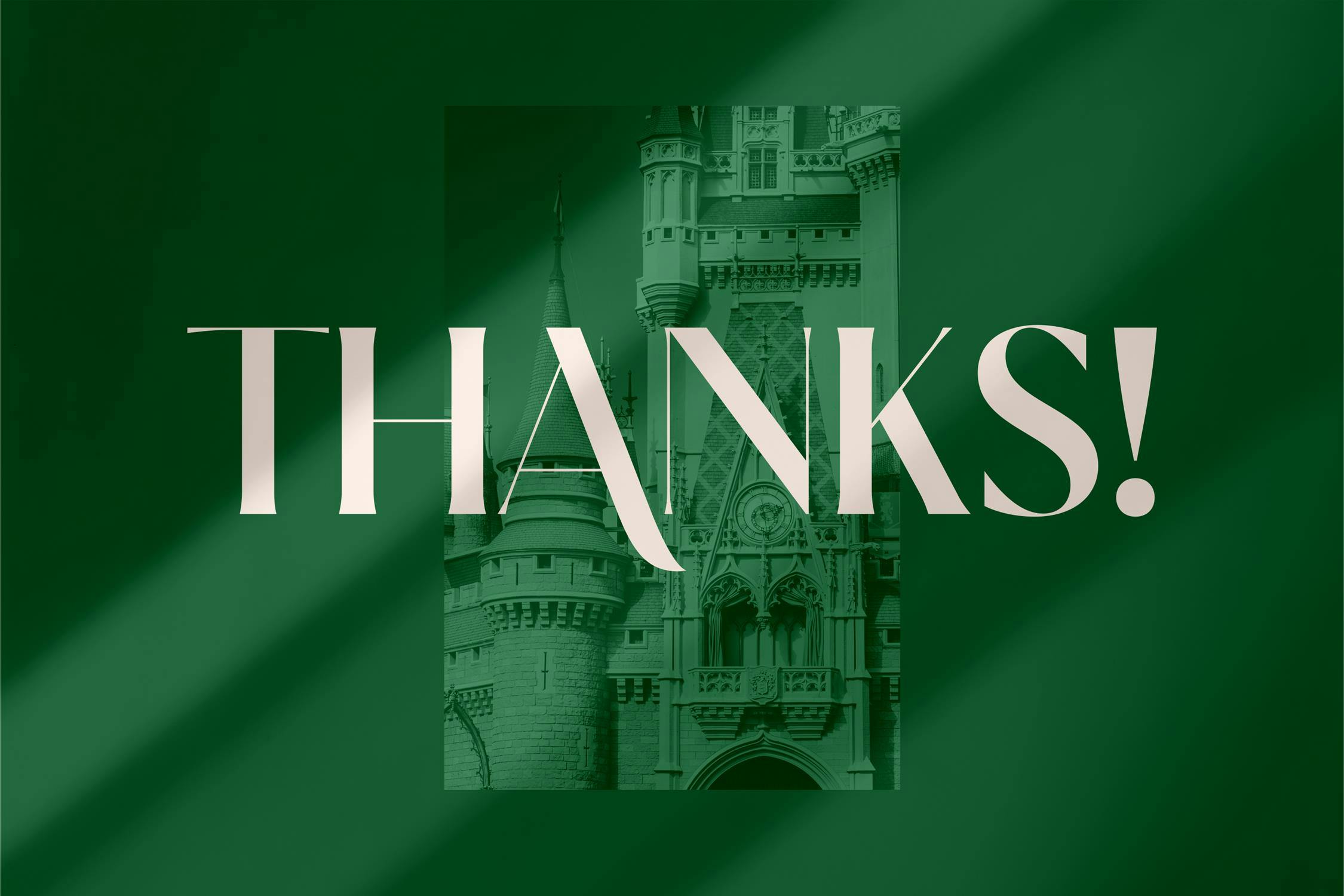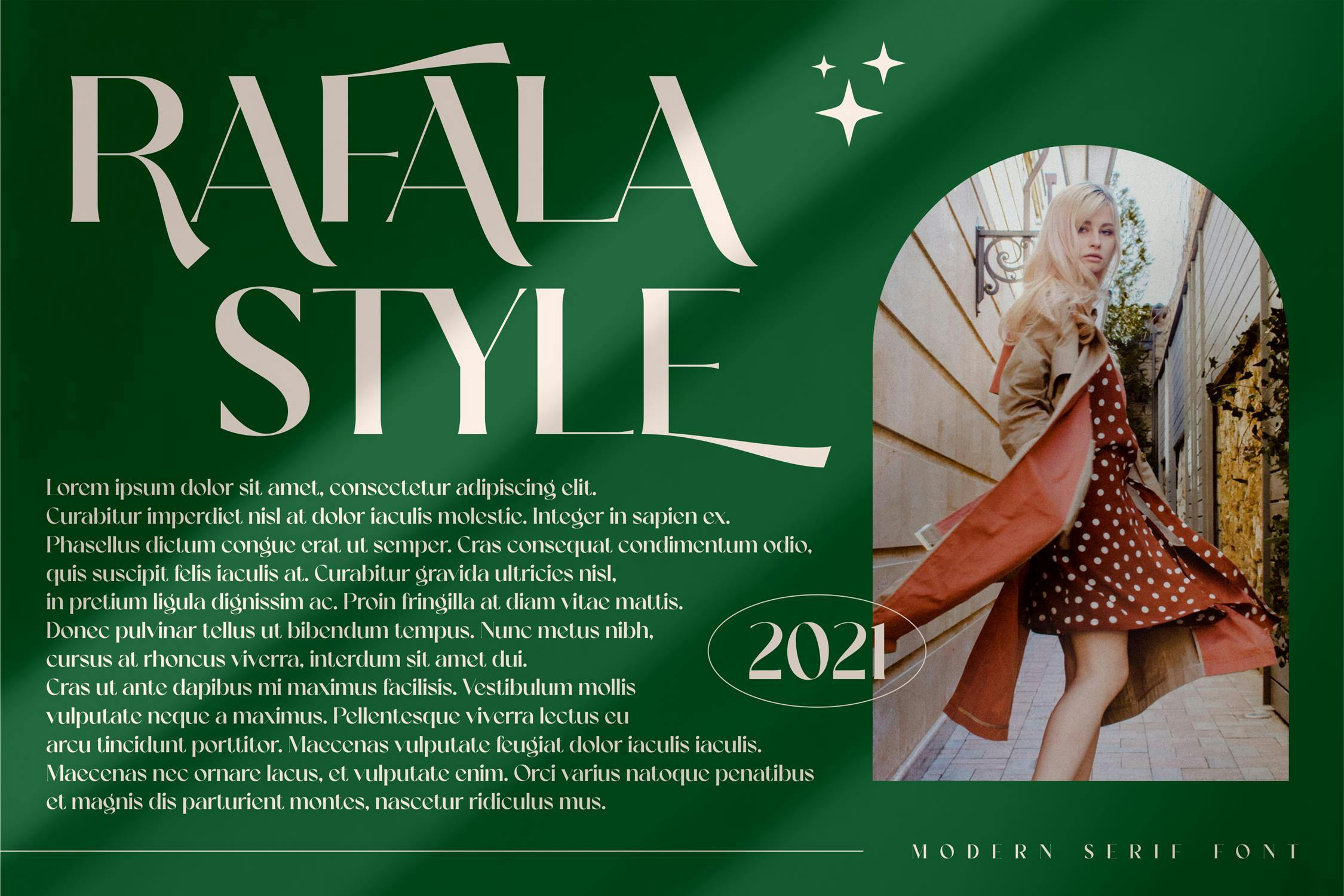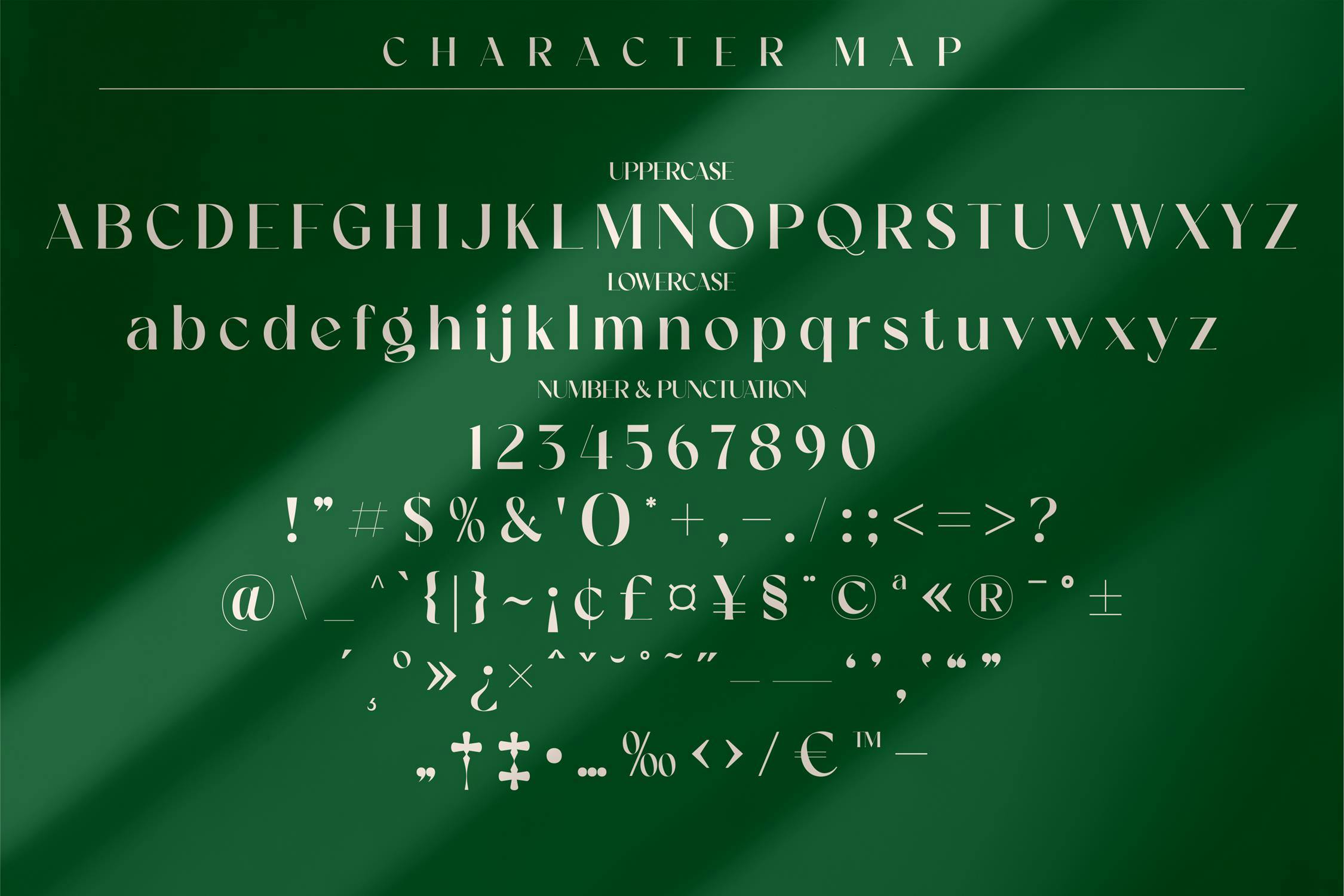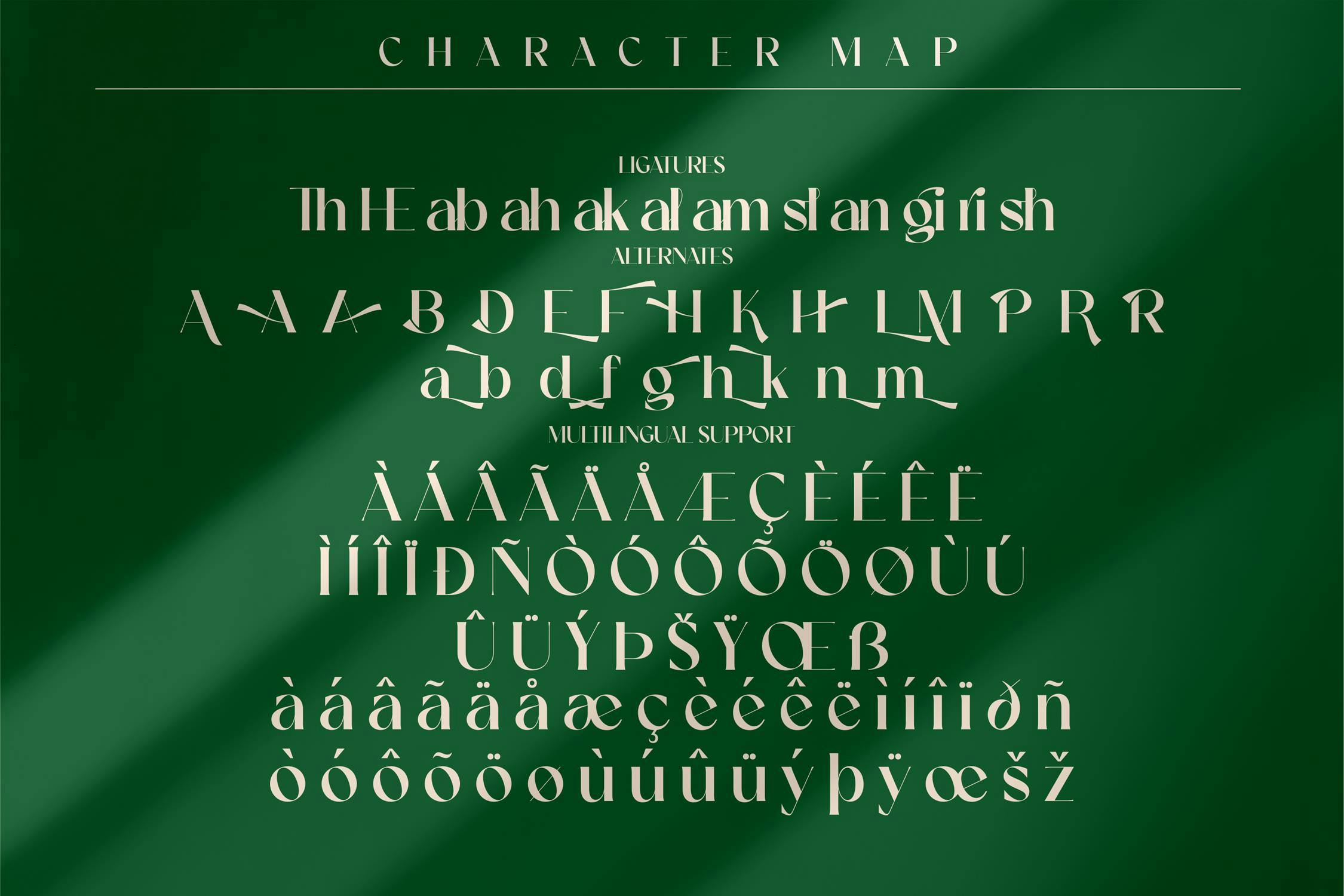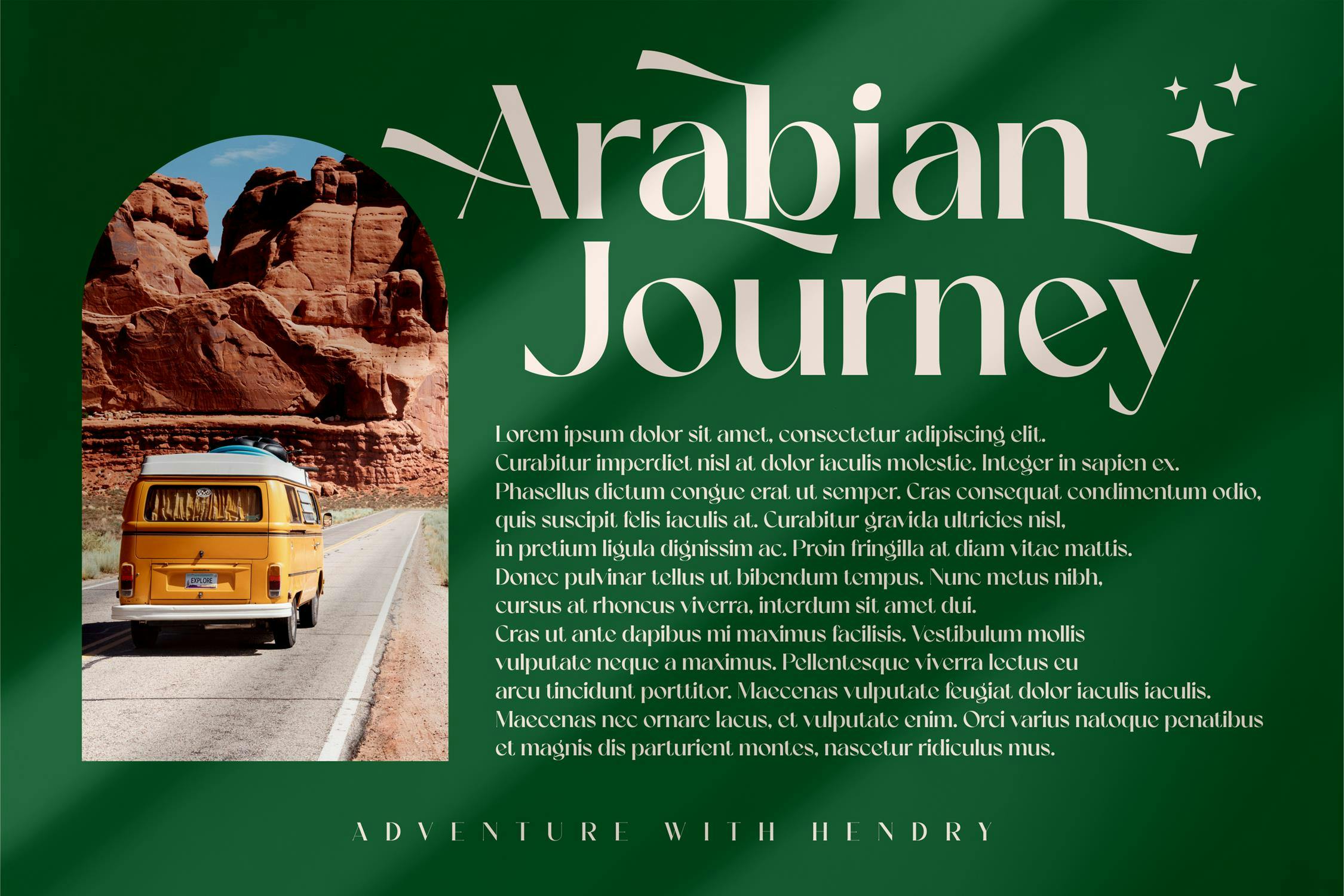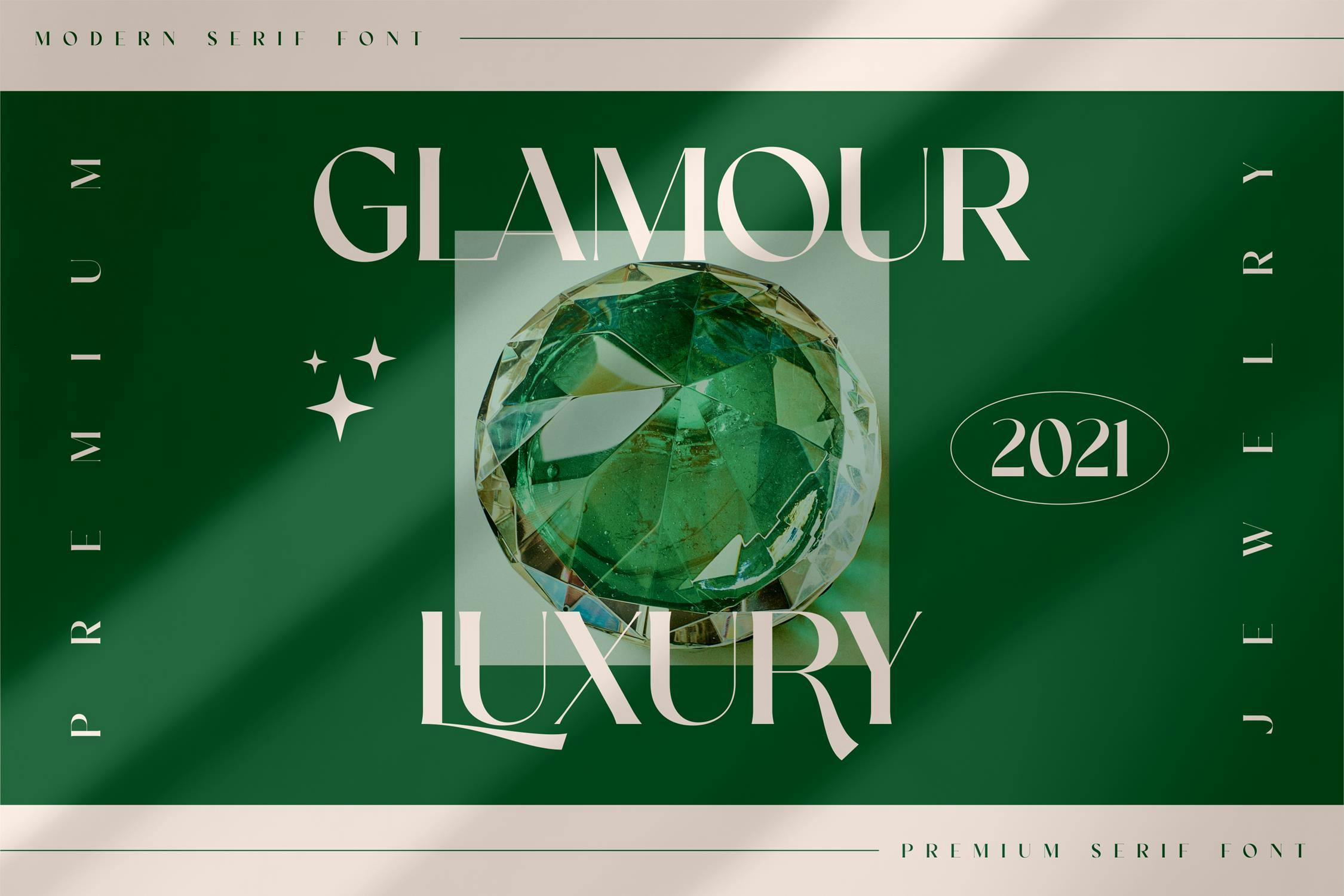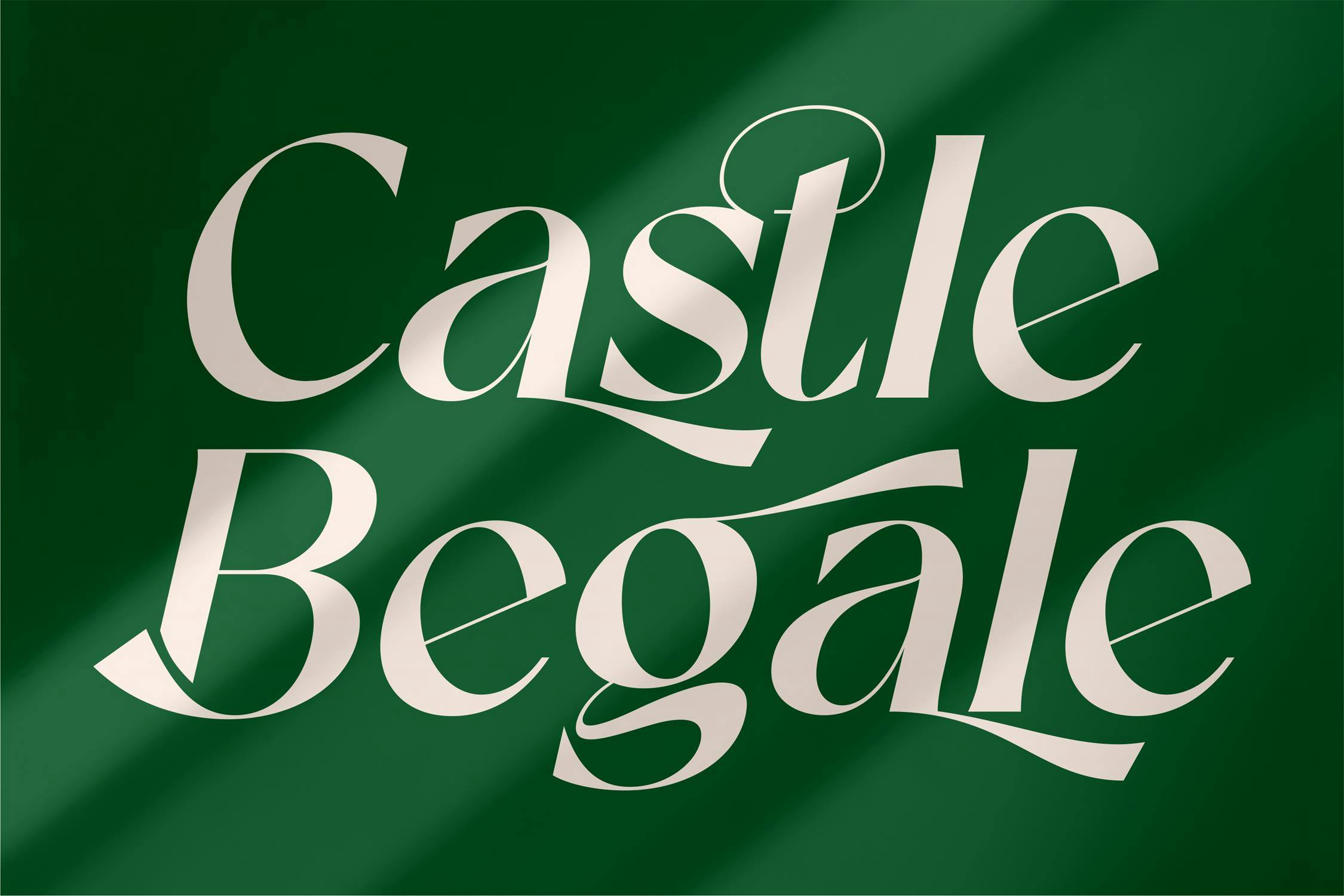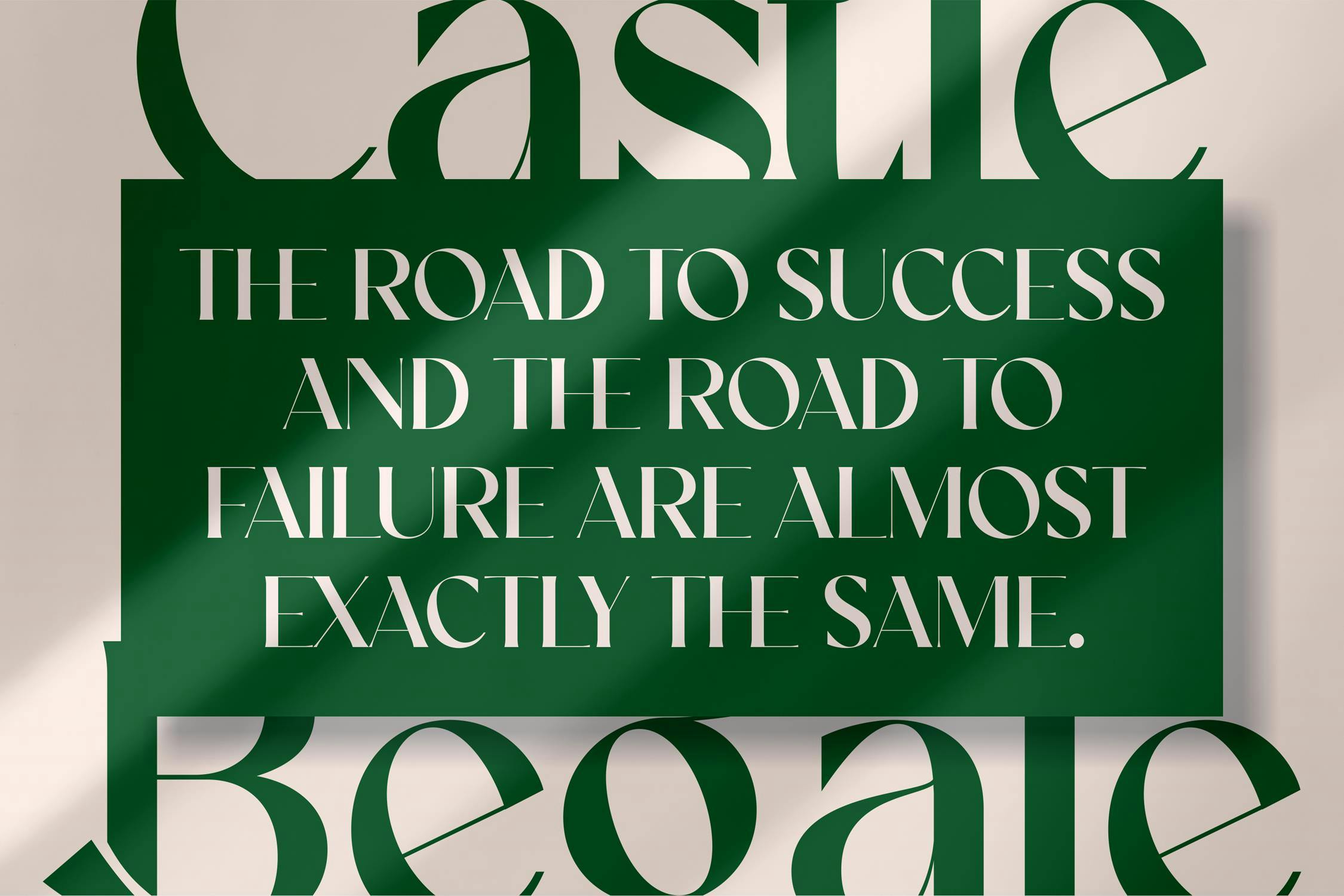
Castle Begale Luxury Serif Font
فونت لوکس Castle Begale، مناسب برای پروژه‌های خلاقانه شما.
سلام خانم‌ها و آقایان، این یکی از فونت‌های ماست که برای تکمیل محصولات خلاقانه دیجیتال و چاپی شما مناسب است.
این فونت برای پوسترها، پست‌های شبکه‌های اجتماعی، برندینگ، پروژه‌های شخصی و غیره عالی است.